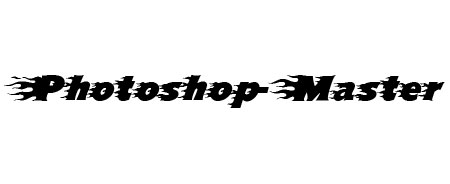
как 2 пальца,пасиба автору cool shrift
Вот Огонь :))
Просто мего шрифт,огромый респект его автору)
а есть такой же, только в обратную сторону?
Прикольный шрифт!
Ухты!!!!!!!!!! Кууууул :D
Просто суперский шрифт! Домо аригато! (большое спасибо!)
Отличный шрифт!
классно то что надо
норм из фильма из уличных